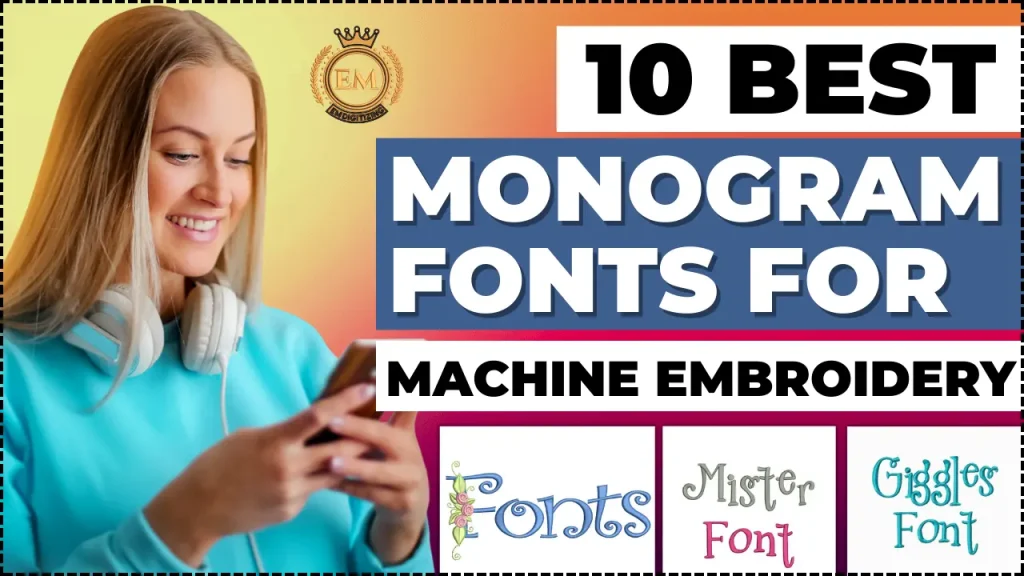
10 I migliori caratteri monogramma per il ricamo a macchina
Il ricamo è stato a lungo un mestiere amato, adding a touch of personalization and elegance to various items. ;
Uno degli elementi chiave che rendono il ricamo davvero unico è la scelta del font. Caratteri monogramma, in particolare, lend a sense of sophistication and individuality to embroidered projects. ;
10 Best Monogram Fonts for Machine Embroidery
Whether you’;stai abbellindo gli asciugamani, vestiario, o accessori, selezionando il monogramma giusto il carattere è fondamentale per ottenere l'estetica desiderata.
Questo articolo esplora il mondo dei migliori font monogrammi per il ricamo a macchina, aiutandoti a navigare tra vari stili, considerazioni, e consigli per trovare il font perfetto per i tuoi progetti.
10 I migliori caratteri monogramma per il ricamo a macchina
Fattori da considerare quando si scelgono i migliori caratteri per monogrammi
La scelta del miglior carattere monogramma è fondamentale per garantire il tuo disegno del ricamo trasmette lo stile e l'eleganza desiderati.
Compatibilità con macchine da ricamo
Prima di lasciarti trasportare da tutti i bellissimi caratteri monogramma disponibili, it’;s crucial to consider whether they’;ri compatibile con il tuo macchina da ricamo.
Supporto di macchine diversi formati di file, quindi assicurati che i caratteri che scegli siano compatibili con la tua attrezzatura.
Dimensioni e scala del monogramma
The size and scale of your monogram will depend on the project you’;ci sto lavorando. Un grande monogramma potrebbe apparire stupendo su una borsa tote, ma potrebbe sopraffare un fazzoletto delicato.
Size and Scale of the Monogram
Dimensioni e scala del monogramma
Considera le dimensioni e le proporzioni del tuo progetto e scegli un carattere che lo integri magnificamente.
Stile di design ed estetica
I caratteri monogramma sono disponibili in un'ampia gamma di stili, dall'elegante e tradizionale all'audace e moderno. Pensa allo stile di design generale e all'estetica che desideri ottenere.
Design Style and Aesthetic
Stile di design ed estetica
Stai cercando un look classico e senza tempo o un'atmosfera contemporanea e audace?
La scelta di un carattere in linea con l'estetica desiderata garantirà un risultato coerente e visivamente gradevole.
Leggibilità e leggibilità
While it’;C'è la tentazione di optare per un carattere monogramma elaborato e intricato, it’;È essenziale considerarne la leggibilità e la leggibilità. Dopotutto, what’;Ecco lo scopo di un monogramma se nessuno può leggerlo?
Assicurati che le lettere siano chiare e facilmente distinguibili, especially if you’;stai ricamando oggetti più piccoli come tovaglioli o polsini di camicie.
Caratteri monogramma classici per un look senza tempo
I caratteri monogramma classici incarnano l'eleganza e un fascino senza tempo, rendendoli perfetti per una vasta gamma di applicazioni, dagli inviti di nozze alla cancelleria personalizzata.
Monogrammi tradizionali in stampatello
Niente dice classico come un monogramma in stampatello. Questi caratteri presentano forme di lettere audaci e semplici che trasudano eleganza e atemporalità.
Traditional Block Letter Monograms
Monogrammi tradizionali in stampatello
Perfetto per aggiungere un tocco raffinato a qualsiasi progetto.
Caratteri monogramma Serif fantasia
Se vuoi aggiungere un tocco di stile al tuo monogramma, i caratteri serif fantasiosi sono la strada da percorrere.
Fancy Serif Monogram Fonts
Caratteri monogramma Serif fantasia
Con i loro serif decorativi e le forme delle lettere eleganti, questi caratteri elevano i tuoi ricami con un tocco di raffinatezza.
Caratteri monogramma impreziositi
Per coloro che amano un po' di brio in più, i caratteri monogramma impreziositi sono una scelta fantastica.
Embellished Monogram Fonts
Caratteri monogramma impreziositi
Questi caratteri presentano dettagli decorati, svolazzi vorticosi, e intricati ricami che creano un senso di lusso e opulenza.
Caratteri monogrammi moderni per un tocco contemporaneo
I migliori caratteri monogrammi moderni apportano un tocco contemporaneo alla personalizzazione tradizionale, unendo linee pulite e design minimalista per un look fresco, aspetto elegante.
Caratteri monogramma puliti e minimalisti
Se preferisci un look elegante e contemporaneo, i caratteri monogramma puliti e minimalisti sono la soluzione migliore.
Con le loro forme di lettera semplici e snelle, questi caratteri apportano un'estetica moderna e sofisticata al tuo progetti di ricamo.
Caratteri monogramma geometrici
I caratteri monogrammi geometrici sono caratterizzati da forme audaci e angoli acuti.
Questi caratteri sono perfetti per coloro che vogliono fare una dichiarazione e aggiungere un tocco di modernità ai propri ricami.
Caratteri monogramma astratti e artistici
2. Versatilità: